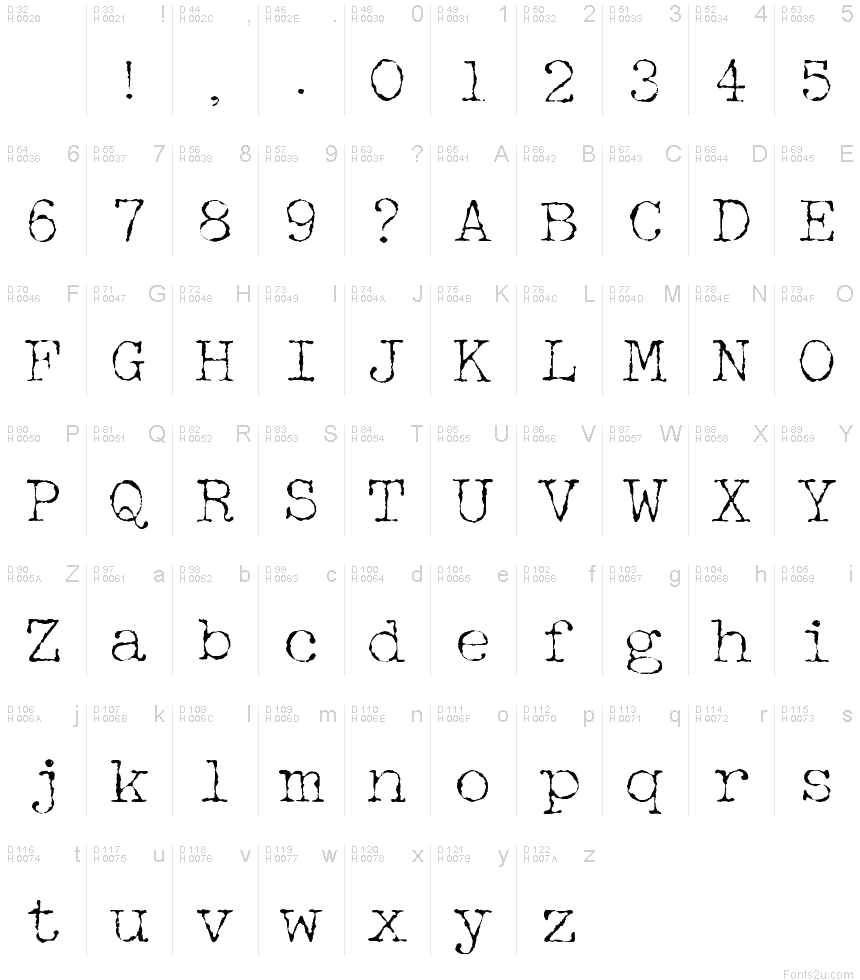
Halbstarke Pica autorstwa Charly’ego Masci to bezpłatny, dekoracyjny krój szeryfowy z efektem erozji. Każda litera wygląda, jakby została zniszczona przez kserokopiarkę, deszcz czy niedbałe traktowanie – z kleksami tuszu i poszarpanymi krawędziami, które dają surowy, analogowy klimat. Odstępy pozostają zaskakująco czytelne, więc zyskujesz ten grunge'owy, ręcznie uszkodzony wygląd bez utraty płynności tekstu.
Dzięki Halbstarke Pica nadasz charakteru plakatom koncertowym, zinom punkowym, tytułom horrorów, grafikom protestacyjnym, okładkom albumów czy odważnym projektom książek. Ten darmowy font świetnie sprawdza się w dużych rozmiarach, gdzie chropowate detale naprawdę ożywają na stronie. Połącz go z geometrycznym krojem bezszeryfowym z rodziny Halbstarke lub neutralnym krojem groteskowym w tekście głównym, aby utrzymać ten chaos w ryzach.